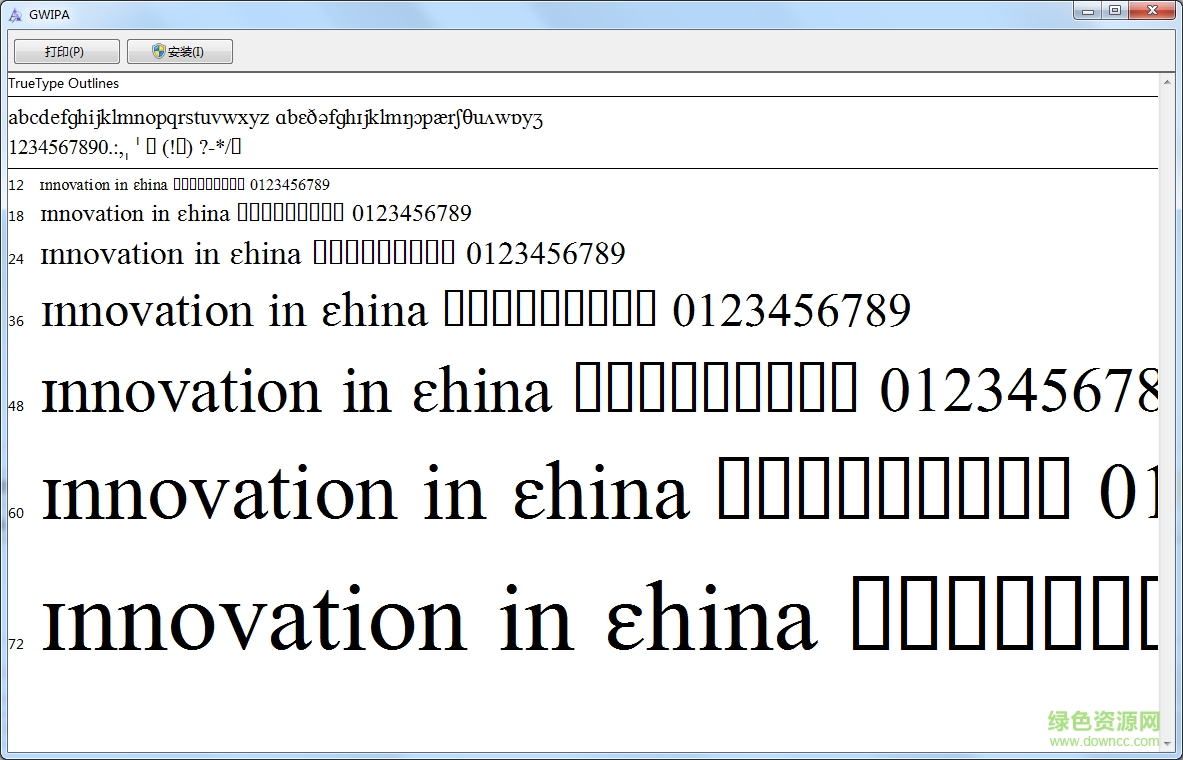
gwipa.ttf是一款非常好用的音標(biāo)字體,用戶下載安裝以后,就可以在鍵盤(pán)上打出英語(yǔ)音標(biāo)了,是不是很炫酷和方便了,如果你也需要的話,趕快到綠色資源網(wǎng)下載體驗(yàn)吧!
它是專門(mén)為中國(guó)人設(shè)計(jì)的gwipa國(guó)際音標(biāo)字體庫(kù),用戶使用它可以在word,excel,powerpoint中通過(guò)鍵盤(pán)直接輸入英語(yǔ)國(guó)際音標(biāo)。